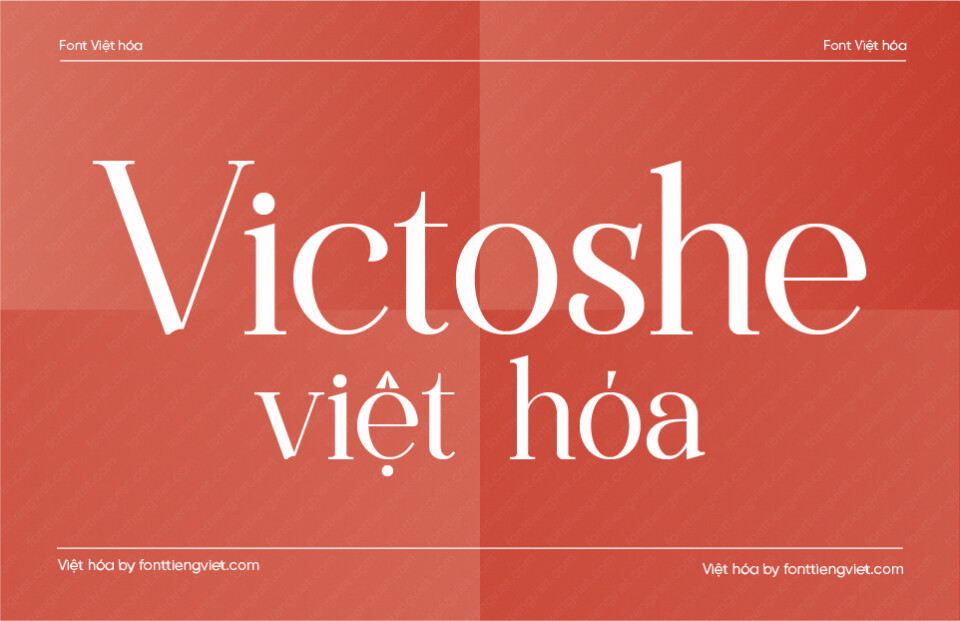
Font Việt hóa 1FTV VIP Victoshe: Lựa chọn hoàn hảo cho thiết kế hiện đạiGiới thiệu về Font Việt hóa 1FTV VIP VictosheTrong thế giới đồ họa kỹ thuật số hiện nay, việc tìm kiếm một bộ chữ vừa mang tính thẩm mỹ cao vừa hỗ trợ đầy đủ tiếng Việt là điều vô cùng quan trọng đối với các nhà sáng tạo. Font Việt hóa 1FTV VIP Victoshe xuất hiện như một giải pháp tối ưu cho những ai đang tìm kiếm sự khác biệt và đẳng cấp. Đây là một bộ Font Miễn Phí được tinh chỉnh kỹ lưỡng về dấu câu, giúp người dùng dễ dàng trình bày nội dung mà không lo lỗi hiển thị. Với phong cách Serif hiện đại kết hợp những đường nét uyển chuyển, bộ phông chữ này mang lại cảm giác sang trọng và chuyên nghiệp ngay từ cái nhìn đầu tiên. Đối với các bạn học sinh và sinh viên, việc sử dụng các bộ chữ được Việt hóa chuẩn xác sẽ giúp bài thuyết trình hoặc dự án cá nhân trở nên thu hút hơn, đồng thời thể hiện sự chỉn chu trong học tập.Đặc điểm nổi bật của Font Việt hóa 1FTV VIP VictosheThiết kế thanh lịch và tinh tếĐiểm nhấn lớn nhất của Font Việt hóa 1FTV VIP Victoshe nằm ở cấu trúc chữ cái hài hòa. Các nét thanh và nét đậm được phân bổ một cách khoa học, tạo nên sự cân bằng thị giác tuyệt vời. Kiểu dáng của Victoshe không quá cứng nhắc như các phông chữ truyền thống mà có sự mềm mại nhất định ở các góc cạnh. Điều này giúp bộ chữ trở nên đa năng, phù hợp cho cả tiêu đề bài viết lẫn các đoạn văn bản ngắn. Khi áp dụng vào các thiết kế bìa sách, thiệp mời hay poster sự kiện nhà trường, bộ chữ này luôn tạo ra một không gian nghệ thuật đầy lôi cuốn.Khả năng ứng dụng linh hoạt trong giáo dụcSự tiện lợi của Font Việt hóa 1FTV VIP Victoshe còn thể hiện ở khả năng tương thích cao với các phần mềm đồ họa phổ biến như Photoshop, Canva hay bộ công cụ văn phòng Microsoft Office. Đối với giáo viên, việc sử dụng bộ chữ này để thiết kế bài giảng điện tử sẽ giúp học sinh dễ dàng tiếp thu kiến thức nhờ sự rõ ràng và đẹp mắt. Các bạn học sinh cũng có thể dùng nó để làm báo tường hoặc tập san lớp, tạo nên những sản phẩm mang dấu ấn cá nhân đậm nét. Việc đã được Việt hóa 100% giúp các từ ngữ có dấu trong tiếng Việt không bị nhảy font, đảm bảo tính thẩm mỹ đồng nhất cho toàn bộ văn bản.Cách sử dụng Font Việt hóa 1FTV VIP Victoshe hiệu quảKết hợp màu sắc và bố cụcĐể Font Việt hóa 1FTV VIP Victoshe thực sự tỏa sáng, bạn nên kết hợp với các tông màu trung tính hoặc pastel nhẹ nhàng. Do đặc tính là một phông chữ VIP có độ chi tiết cao, Victoshe thường hoạt động tốt nhất khi được đặt trên các nền đơn giản hoặc hình ảnh có độ tương phản thấp. Bạn có thể sử dụng chữ viết hoa cho các tiêu đề lớn để tạo sự bùng nổ về thị giác, sau đó dùng kiểu chữ thường cho các dòng mô tả phụ. Lưu ý rằng không nên nhồi nhét quá nhiều hiệu ứng đổ bóng phức tạp, vì bản thân các đường nét của Victoshe đã đủ tinh tế để tự khẳng định giá trị của mình.Lưu ý khi cài đặt và sử dụngViệc cài đặt bộ chữ này vô cùng đơn giản, bạn chỉ cần tải về và giải nén tệp tin định dạng .ttf hoặc .otf. Sau khi cài đặt vào hệ thống, bạn có thể bắt đầu sáng tạo ngay lập tức. Hãy luôn kiểm tra lại khoảng cách giữa các chữ cái (kerning) để đảm bảo văn bản được trình bày đẹp mắt nhất. Việc sử dụng những bộ chữ chất lượng như thế này không chỉ nâng cao kỹ năng thiết kế mà còn giúp các bạn trẻ hiểu thêm về giá trị của nghệ thuật chữ viết trong đời sống hiện đại.Tổng kết về bộ phông chữ 1FTV VIP VictosheCó thể thấy, Font Việt hóa 1FTV VIP Victoshe là một tài nguyên quý giá dành cho cộng đồng thiết kế tại Việt Nam. Nó không chỉ đáp ứng yêu cầu về mặt kỹ thuật mà còn chạm đến cảm xúc thẩm mỹ của người xem. Dù bạn là một designer chuyên nghiệp hay một học sinh đang tập tành thiết kế, bộ chữ này chắc chắn sẽ là người bạn đồng hành tin cậy. Nếu bạn đang tìm kiếm thêm nhiều lựa chọn khác để làm phong phú kho tài nguyên của mình, hãy truy cập Font Miễn Phí, Font Việt Hóa, Font Việt hóa 1FTV VIP Victoshe để sở hữu ngay những bộ chữ đỉnh cao nhất cho dự án sắp tới của mình.
Font Việt hóa 1FTV VIP Victoshe